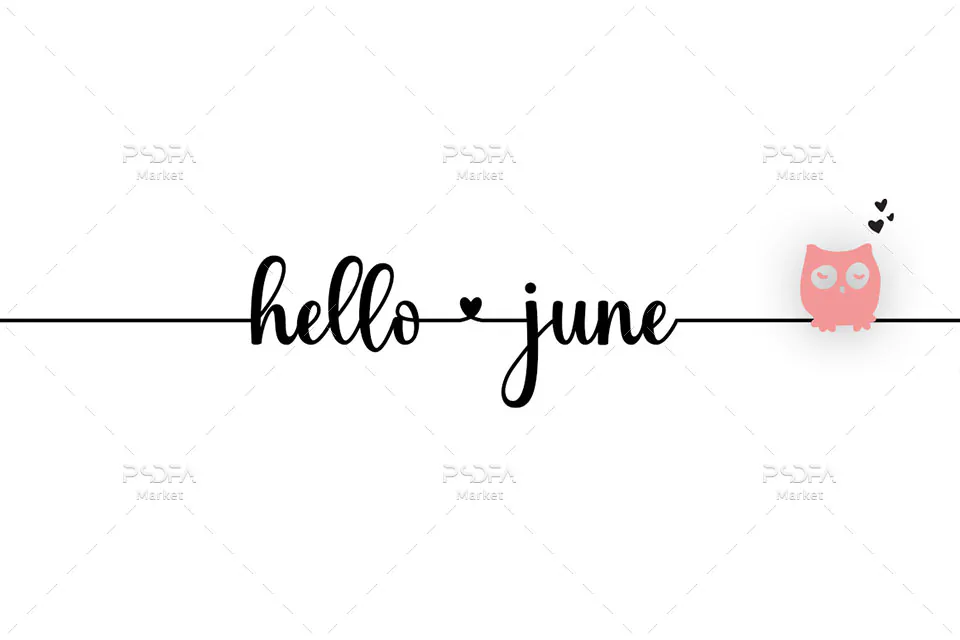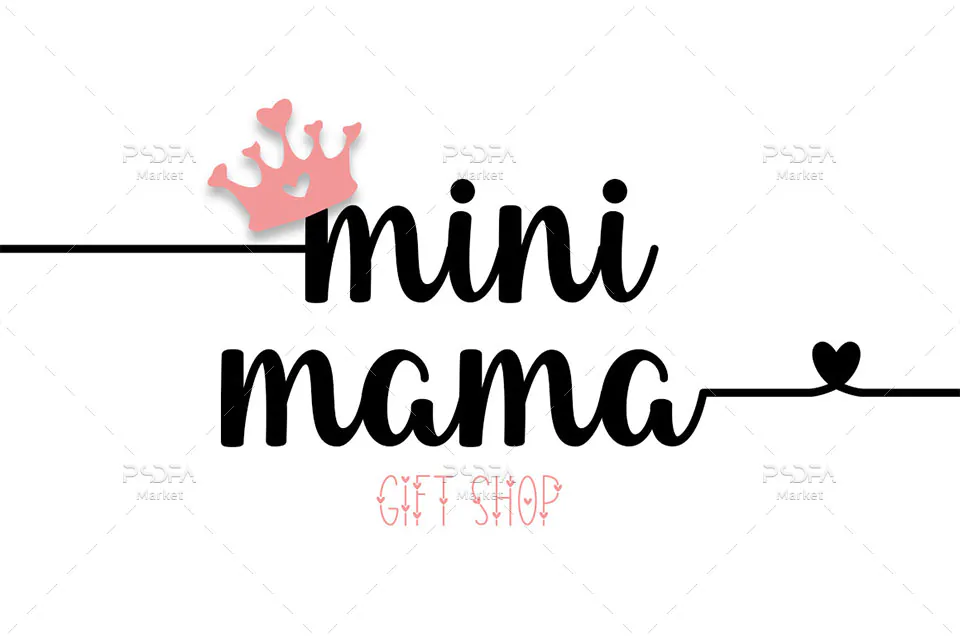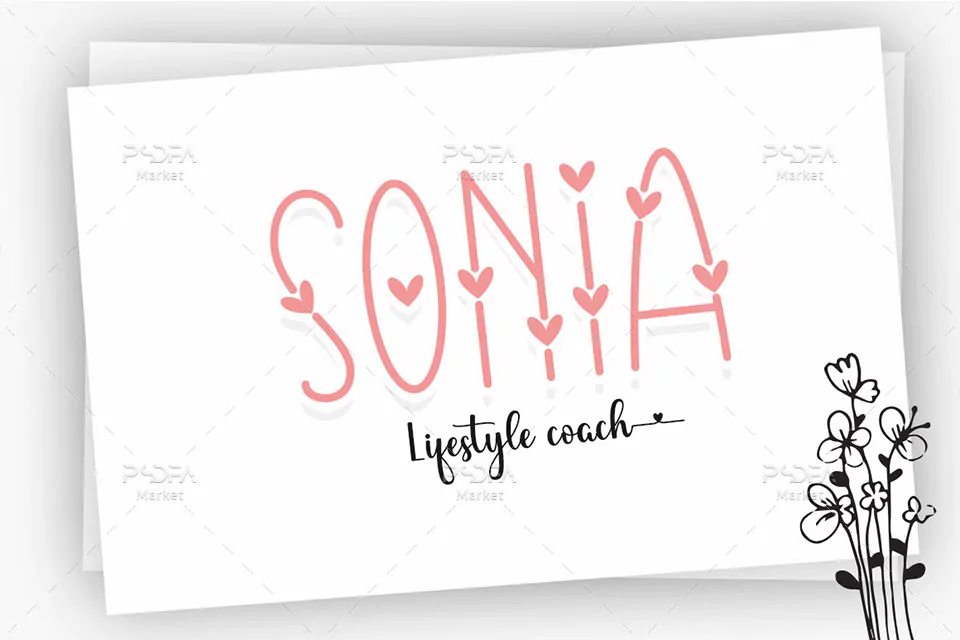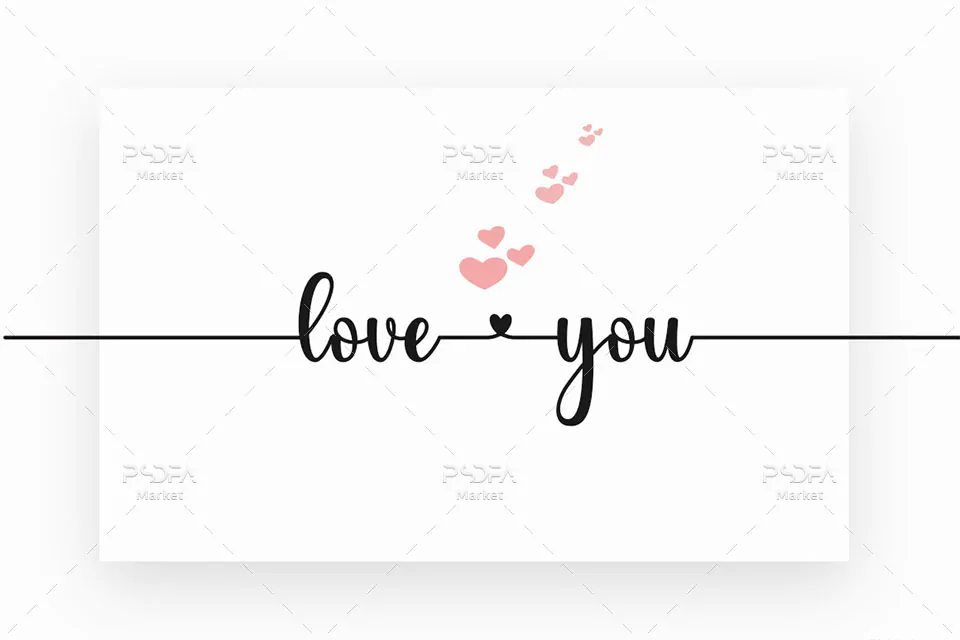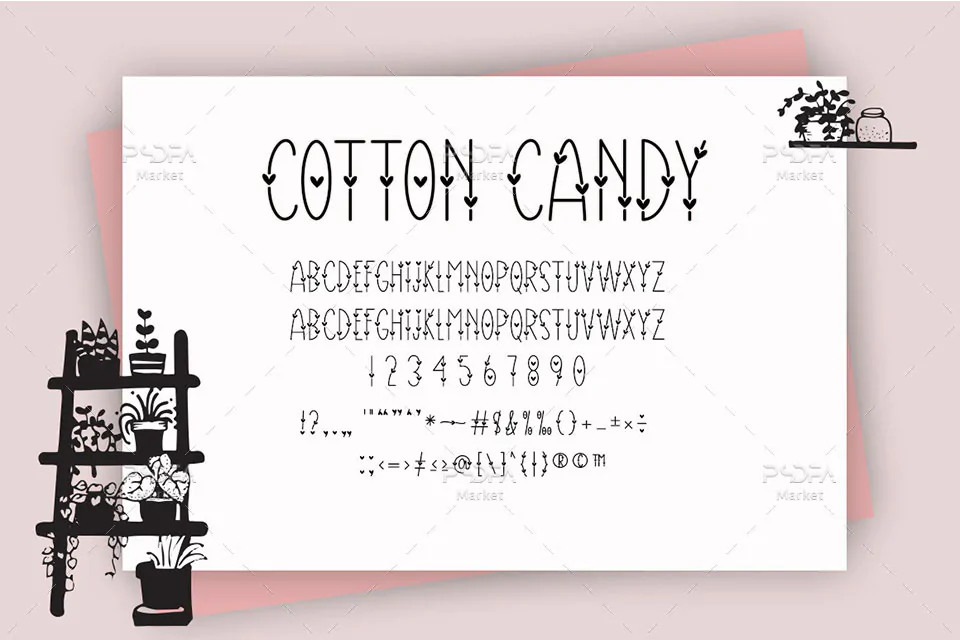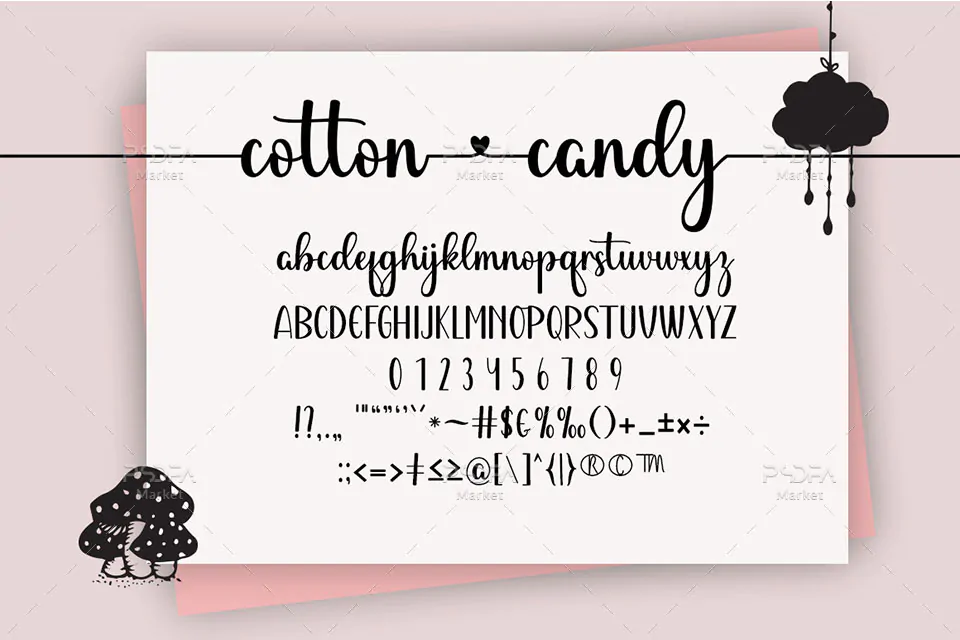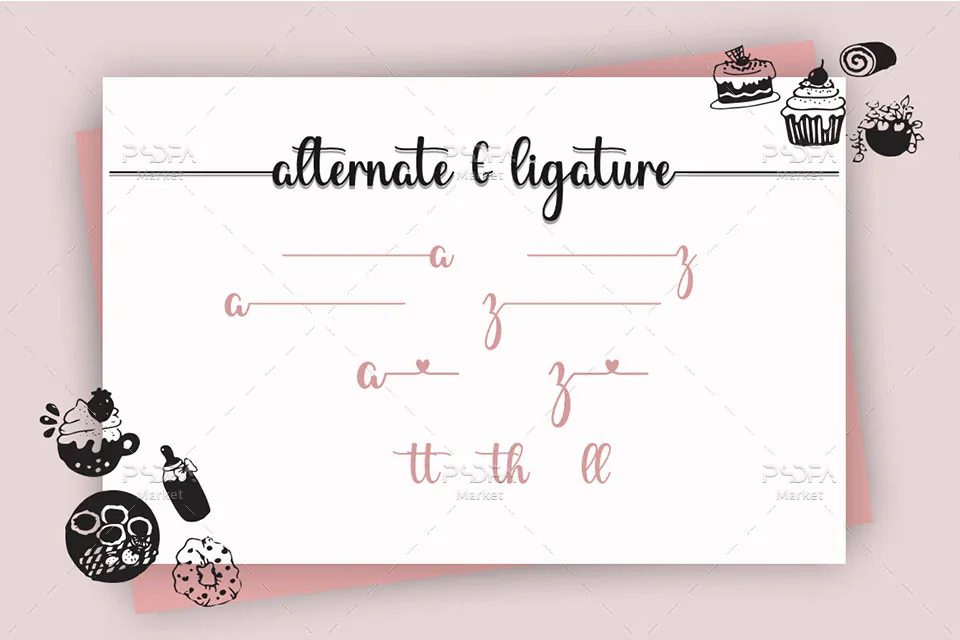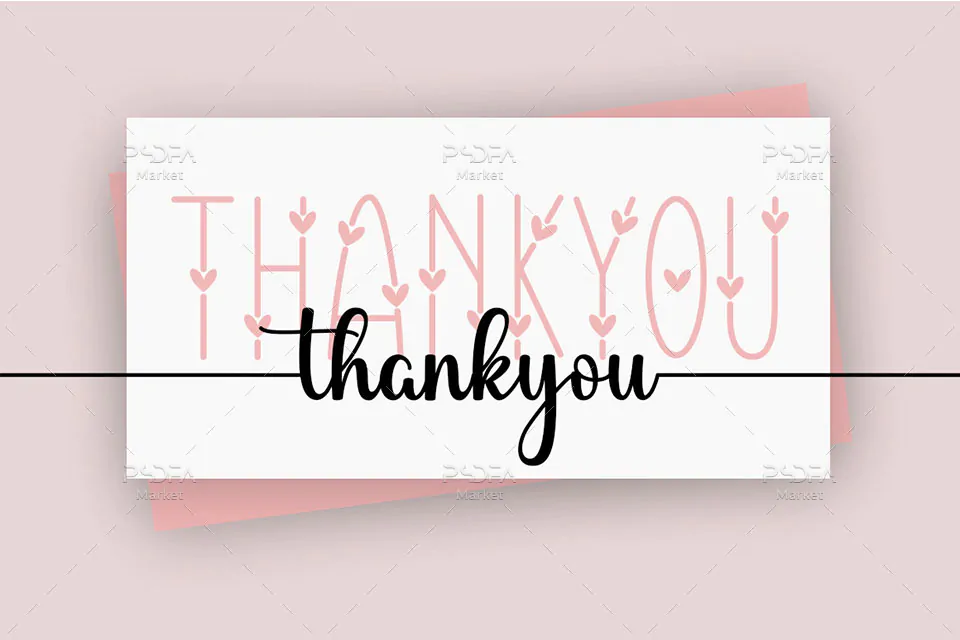
فونت انگلیسی فانتزی دخترانه Cotton Candy یک قلم زیبای عاشقانه و رمانتیک به همراه وکتور عناصر طراحی است که مناسب جهت استفاده در طرح و پروژههای گرافیکی مختلف به خصوص طرحهای ولنتاین میباشد. این فونت زیبا در قالب 4 فایل OTF, TTF در فایل محصول قرار دارد که با نصب یکی از این دو فرمت در پوشه فونتهای سیستم میتوانید از این فونت انگلیسی در تمام نرم افزارهای گرافیکی و تایپ متون همچون فتوشاپ، افتر افکت، پریمیر، ورد، پاورپوینت و … استفاده کنید.
فونت Cotton Candy در وزن معمولی (Regular) و دو نسخه طرح دار و ساده طراحی شده است که میتوانید از آن در طراحی انواع کارت تبریک، کارت پستال، کارت ویزیت، کارت عروسی، کاور آلبوم موزیک، طراحی انواع بنر، پوستر، تراکت، تقویم و دیگر طرحهای گرافیکی استفاده کنید.
- نام فونت: Cotton Candy